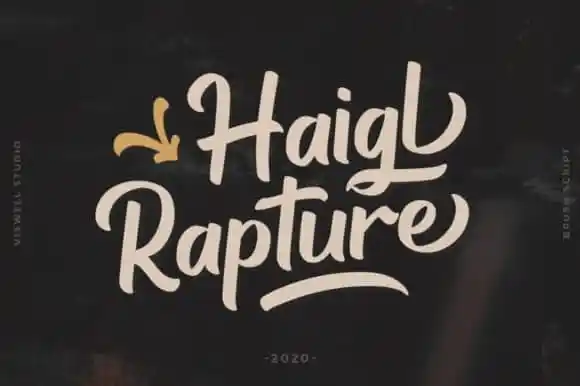
Descubra a nova Haigl Rapture Script Font que está disponível agora! Esta fonte de estilo script foi projetada para combinar elementos de fantasia com traços de tinta escrita à mão, um toque elegante e uma forma fluida. Desenvolvida pelo agamous, ela é perfeita para os seus trabalhos favoritos. A Haigl Rapture Script Font tem um estilo distintivo e eterno que você certamente vai amar e pode usá-la para criar designs impressionantes. Seja criativo com esta fonte única e única, ela irá tornar seu trabalho ainda mais especial. Não perca tempo, está disponível em sua categoria de fontes script na 99designs.